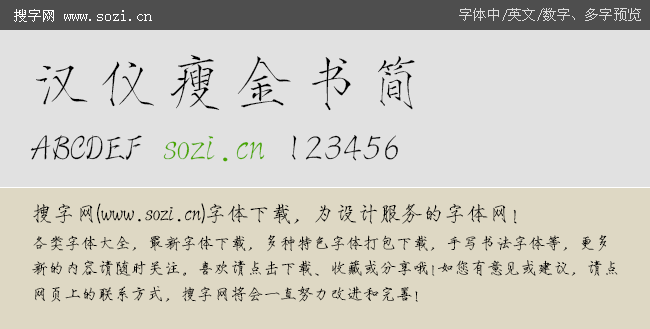
漢儀瘦金書簡(jiǎn)
搜字網(wǎng)提供一款書法字體漢儀瘦金書簡(jiǎn)字體下載,瘦金體為宋徽宗趙佶所創(chuàng),是書法史上的一項(xiàng)獨(dú)創(chuàng)。瘦金體運(yùn)筆飄忽快捷,筆跡瘦勁,至瘦而不失其肉,轉(zhuǎn)折處可明顯見到藏鋒,露鋒等運(yùn)轉(zhuǎn)提頓痕跡,是一種風(fēng)格相當(dāng)獨(dú)特的字體。適合字貼、招貼、書法畫冊(cè)設(shè)計(jì)應(yīng)用。